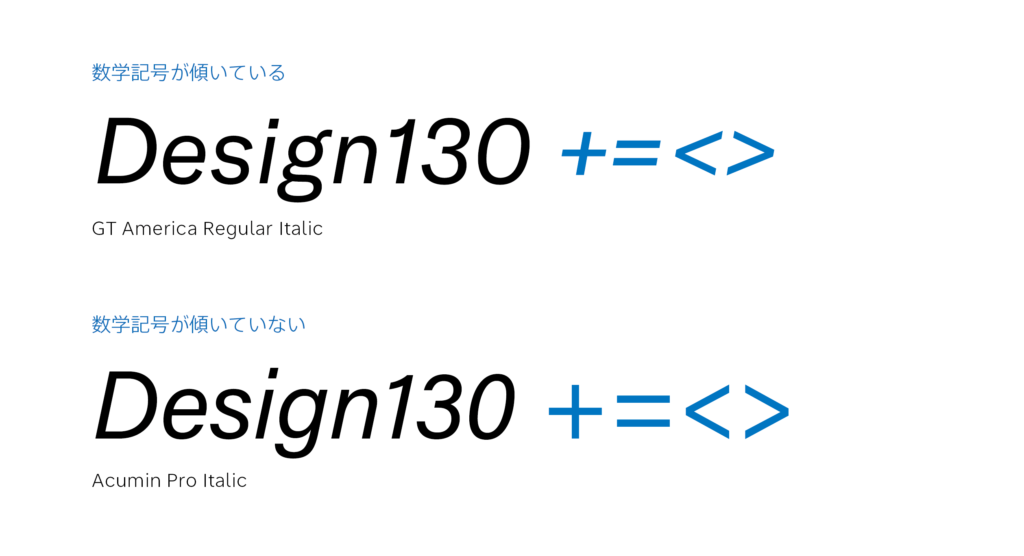
欧文イタリック07「傾ける文字・傾けない文字」
本シリーズの前回記事「イタリックの傾斜」では傾き具合がもたらす印象の差について書きましたが、今回はひとつのフォントの文字セットの中でどのグリフを傾けるのかについてお話ししたいと思います。
イタリックは横に傾いているデザインが一般的ですが、フォント内の全ての文字が傾いているというわけではありません。フォントに含まれているグリフをひとつひとつ見ていくと正体のままのデザインを保っているグリフもいくつかあることがあります。
どのグリフを傾けるのかというのはデザイナー個人の判断によるところも大きいです。A-zや数字などの基本的なグリフは傾いていることがほとんどですが、記号類の扱いについては書体によって様々です。数学記号(+=<>)など本文に登場してイタリックで組まれる頻度の低いグリフは傾けない選択をされることが多い印象があります。
会社としてルールを制定し、リリースするフォント全てにおいて傾斜させるグリフを揃えているところもある一方で、書体の用途によって柔軟に対応している会社もあります。フォント販売サイトのプレビューなどで色々な文字を入力して、書体ごとの違いを見てみるのも面白いかもしれません。